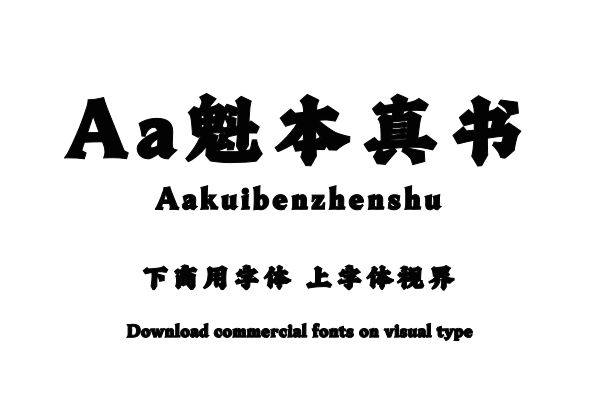
这款字以《魁本对相四言杂字》为设计参考,笔画造型潇洒有力,抑扬顿挫,起笔收笔粗重醒目、化曲为直,字形中宫稍紧,左收右放、内收外放,加强了装饰感,又还原书法本味。购买须知:“下载服务费”与“字体VIP”所获得字体 仅用于个人非商用, 商用请联系付费授权。本字体为电脑用字,手机没有root权限不支持直接手机换字(手机如何root,请自行百度搜索教程)。购买前请先 了解清楚后再付款 ,字体为虚拟产品无法回收 一旦购买不支持退款。